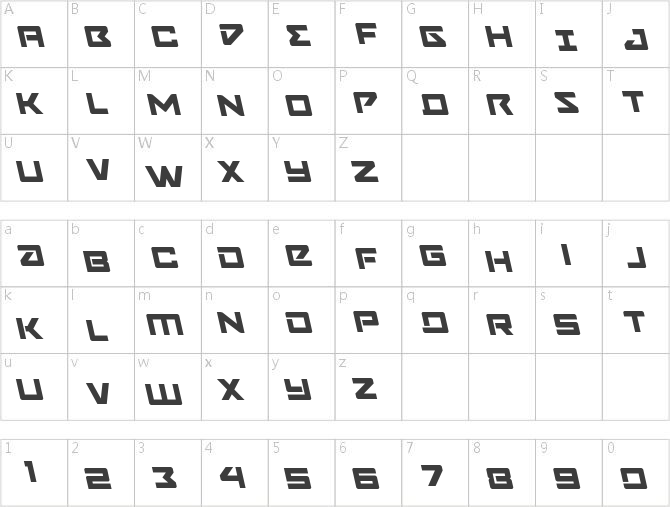
Navy Cadet Leftalic 詳情頁
Navy Cadet Leftalic
Navy Cadet Leftalic字體字庫是一款讓人賞心悅目、百看不厭的英文字體,適合各類廣告和產(chǎn)品包裝設(shè)計應(yīng)用,字體大小0.03MB,格式為ttf字體,上傳用戶是Honor,作者/版權(quán)方為未知